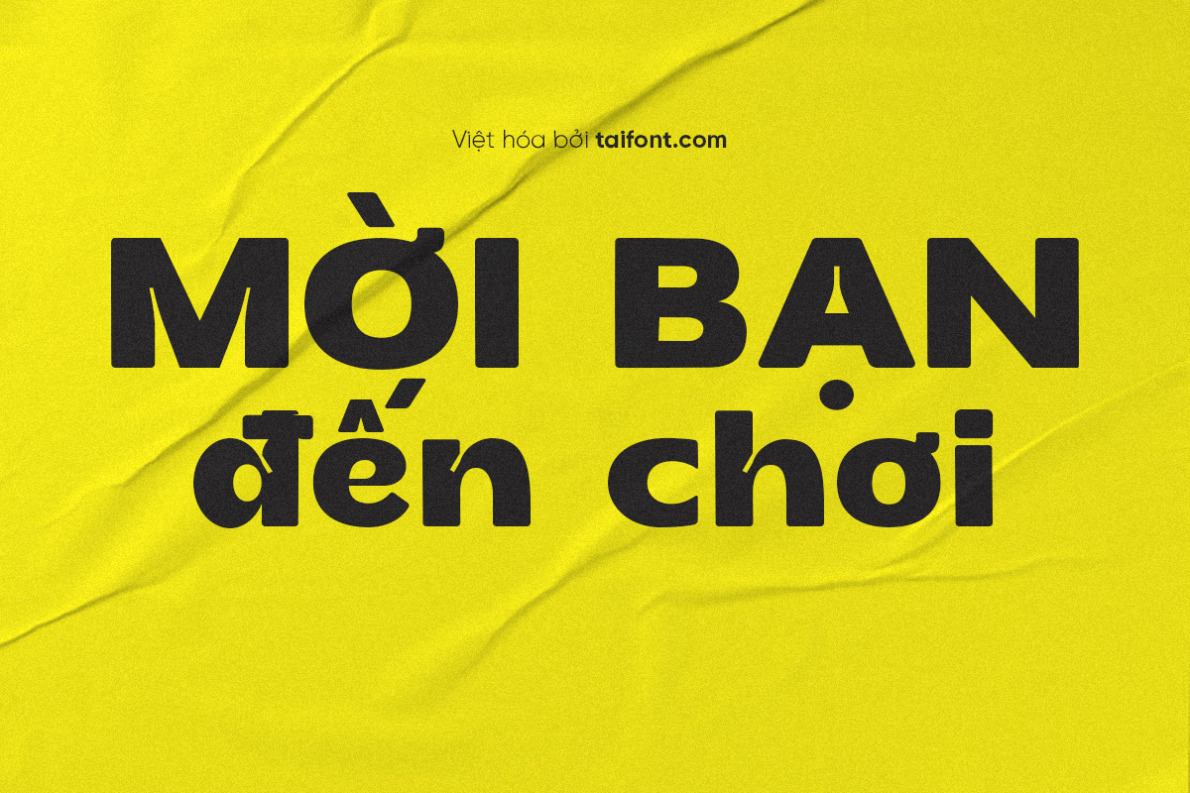
Font Việt hóa ẩm thực đẹp cho thiết kế
Font Việt hóa ẩm thực đẹp cho thiết kế, bạn chắc chắn sẽ thích.
Khi thiết kế các ấn phẩm quảng cáo, menu, hoặc bao bì sản phẩm ẩm thực, việc chọn font chữ phù hợp không chỉ giúp sản phẩm nổi bật mà còn tạo ra sự kết nối với khách hàng. Bộ sưu tập font chữ Việt hóa dưới đây sẽ giúp bạn tạo ra những thiết kế vừa đẹp mắt, vừa ấn tượng. Hãy cùng khám phá những font chữ này và ứng dụng của chúng trong ngành thiết kế ẩm thực!
1. Font TF JT Olifer SemiBold
• Đặc điểm: Font không chân, nét đậm, bo tròn.
• Ứng dụng: Font TF JT Olifer SemiBold là lựa chọn tuyệt vời cho các thiết kế ẩm thực hiện đại và năng động. Với nét đậm, font này rất thích hợp để sử dụng trong các tiêu đề của menu, biển hiệu quán ăn hoặc các chương trình khuyến mãi. Đặc biệt, với kiểu dáng không chân và bo tròn, font chữ này mang lại cảm giác trẻ trung và dễ tiếp cận, giúp thu hút sự chú ý của khách hàng ngay từ cái nhìn đầu tiên.
2. Font TF Hippie Mods
• Đặc điểm: Font tròn, mập, dễ thương.
• Ứng dụng: TF Hippie Mods là một font chữ tuyệt vời cho những món ăn hoặc cửa hàng ẩm thực mang phong cách dễ chịu, vui nhộn. Font tròn, mập sẽ tạo cảm giác thân thiện và dễ gần, rất phù hợp cho các quán cà phê, trà sữa, hoặc các cửa hàng đồ ăn nhanh. Bạn có thể sử dụng font này cho các menu, poster hoặc quảng cáo sự kiện để thu hút đối tượng khách hàng trẻ tuổi, năng động.
3. Font TF Mayura
• Đặc điểm: Font ngộ nghĩnh, béo tròn.
• Ứng dụng: Font TF Mayura mang đến một phong cách ngộ nghĩnh và dễ thương, với đường nét béo tròn, tạo cảm giác vui tươi và hứng khởi. Đây là một lựa chọn lý tưởng cho các thiết kế dành cho các cửa hàng ẩm thực phục vụ món ăn vặt, tráng miệng, hoặc các sản phẩm phục vụ giới trẻ. Bạn có thể áp dụng font này vào các thiết kế menu, bao bì bánh kẹo, hoặc các biển hiệu quán ăn có phong cách vui vẻ, sáng tạo.
4. Font UTM Cooper
• Đặc điểm: Font miễn phí, tròn và nét đậm.
• Ứng dụng: Font UTM Cooper là một font miễn phí dễ sử dụng và có độ tương phản cao với nét đậm, giúp nội dung dễ đọc và thu hút. Font này rất phù hợp cho các thiết kế menu, biển hiệu quán ăn hoặc các chiến dịch quảng cáo ẩm thực. Với thiết kế tròn và dễ đọc, font UTM Cooper mang lại cảm giác thân thiện, dễ tiếp cận và rất phù hợp cho các cửa hàng ăn uống có không gian gần gũi và đơn giản.
5. Font TF Brexon
• Đặc điểm: Đường nét đậm mạnh mẽ, phong cách Vintage.
• Ứng dụng: Font TF Brexon là một font chữ mang phong cách Vintage với những đường nét đậm mạnh mẽ, giúp làm nổi bật tiêu đề và các yếu tố quan trọng trong thiết kế. Đây là lựa chọn lý tưởng cho các nhà hàng sang trọng, các quán ăn mang phong cách cổ điển hoặc các thương hiệu ẩm thực yêu thích sự lịch lãm, cổ điển. Bạn có thể sử dụng font TF Brexon để thiết kế menu, poster quảng cáo, hoặc bao bì sản phẩm, tạo điểm nhấn mạnh mẽ và thu hút khách hàng ngay từ cái nhìn đầu tiên.
Kết luận:
Mỗi loại font chữ đều có những đặc điểm riêng biệt, phù hợp với các loại hình và phong cách ẩm thực khác nhau. Việc lựa chọn font chữ đúng sẽ giúp bạn tạo ra những thiết kế đẹp mắt, dễ nhận diện và phù hợp với đối tượng khách hàng mà bạn hướng đến. Dù là phong cách hiện đại, dễ thương hay cổ điển, bộ sưu tập font chữ Việt hóa trên sẽ giúp bạn xây dựng thương hiệu ẩm thực độc đáo và nổi bật. Hãy thử ngay và tạo nên những thiết kế ấn tượng cho thương hiệu của bạn!